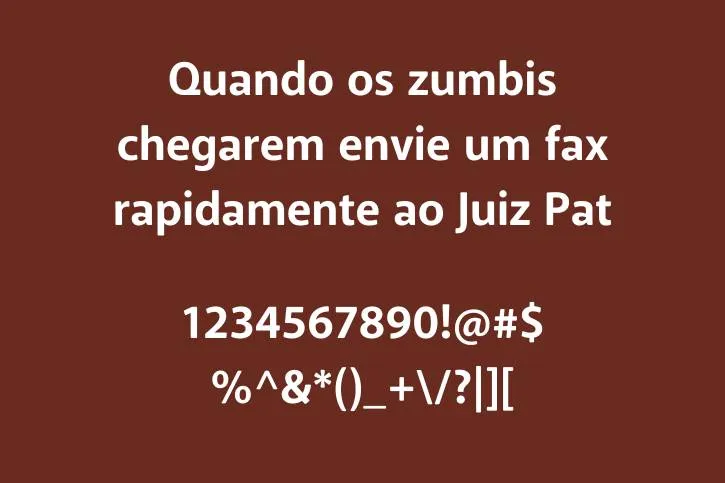
A fonte Anago é uma fonte sem serifa moderna e versátil, conhecida por sua simplicidade e projetada por Neil Summerour. Projetado com precisão e atenção aos detalhes, oferece uma estética contemporânea que se adapta a uma variedade de contextos de design. Com linhas limpas e formas geométricas equilibradas, proporciona uma experiência de leitura clara e confortável.
Uma das principais características é a sua excelente legibilidade, mesmo em tamanhos menores ou em condições de iluminação desafiadoras. Cada personagem é cuidadosamente desenhado para garantir uma forma nítida e clara. Ele foi projetado para oferecer uma experiência de design consistente e profissional.
Exibição da Fonte Anago
Melhores Recursos da Fonte Anago
Variedade de gramaturas e estilos: Oferece uma ampla gama de gramaturas e estilos, desde variantes mais leves até mais ousadas.
Legibilidade excepcional: Cada um de seus caracteres é cuidadosamente projetado para garantir excelente legibilidade. Você também pode usá-lo emparelhando-o com a fonte Lactosa.
Design coeso e harmonioso: Seu conjunto é desenhado com consistência e coesão, garantindo uma estética visualmente agradável.
Versatilidade de aplicação: Pela sua simplicidade e design contemporâneo, é altamente versátil e pode ser utilizado em diversos contextos de design.
Qualidade de design consistente: cada caractere é projetado com precisão e atenção aos detalhes, resultando em uma fonte que oferece uma experiência de design confiável.
Aplicativos que Usam a Fonte Anago
- Convites de festas infantis.
- Cartões de aniversário e saudações.
- Materiais escolares e educativos.
- Embalagens de produtos relacionados a confeitaria.
- Postagens em redes sociais com temáticas lúdicas.
- Criação de logotipos para negócios criativos.
- Decoração de festas e eventos temáticos.
- Projetos de artesanato e DIY.
- Páginas de scrapbook e álbuns de memórias.
- Elementos gráficos em websites e blogs divertidos.
Família de Fontes per Anago
- Anago Regular
- Anago Bold
- Anago Semi Bold
É uma fonte sem serifa moderna e versátil, conhecida por sua simplicidade e desenhada por Neil Summerour.
Com linhas limpas e formas geométricas equilibradas, proporciona uma experiência de leitura clara e confortável.